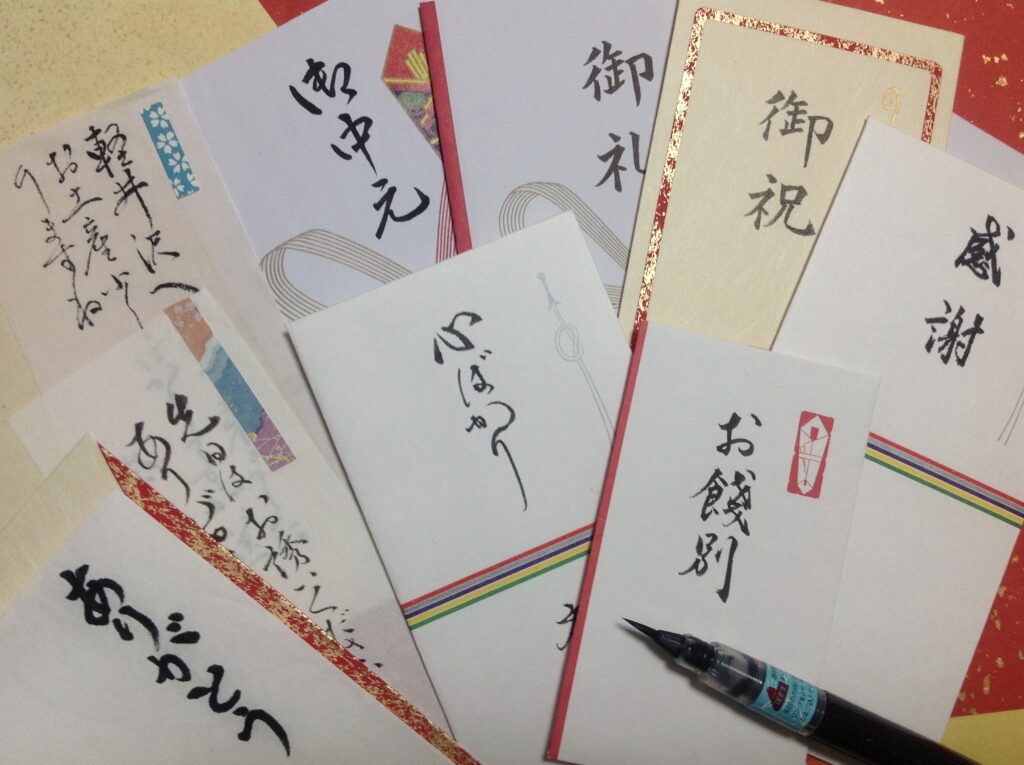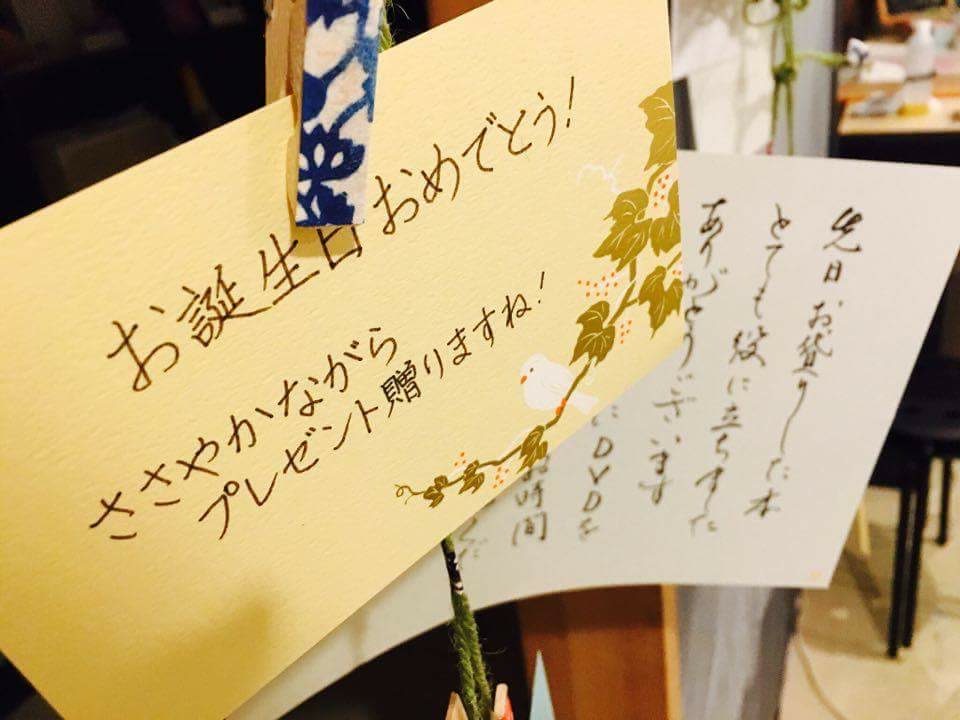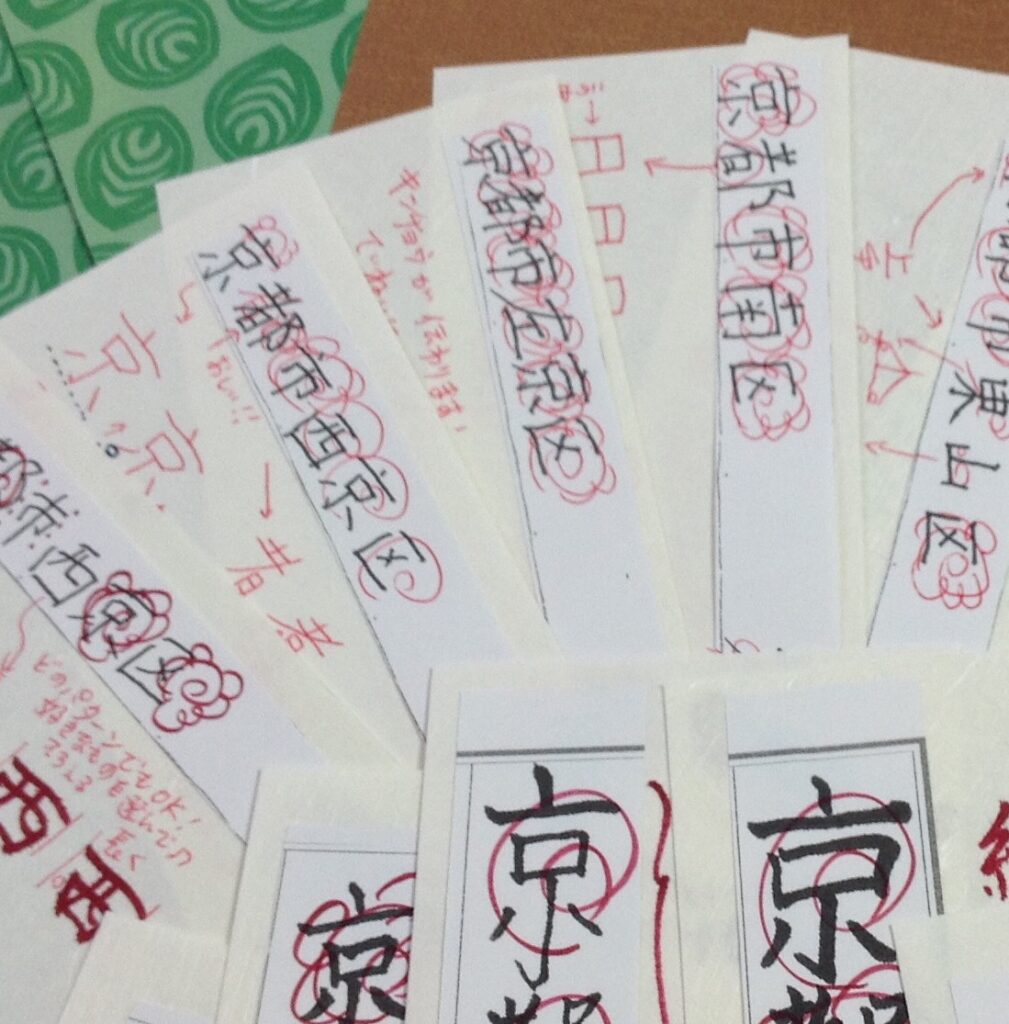
筆文字デザイン・サイン作成
書家・KISEN-髙橋琦泉-
Calligraphy design
企業、店舗、商品などの筆文字ロゴ・題字・屋号、
商品パッケージなどの筆文字ロゴデザインについて承っております。
毛筆デザインとセットで水墨画での挿絵や文字を絵にするなども可能です。
このほか、
企業理念、イベント使用のタイトルなどのほか、
個人様のお名刺、命名書、手紙代筆や贈り物などのラッピングデザイン、
WEBサイトのタイトル、SNSのプロフィール画像やアイコンデザインなど、
さまざまなご要望に合わせたオリジナルデザインをご提供し、
魅力を最大限に引き出すお手伝いを
みなさまのご要望に応じて、心を込めて制作しています。
Name design
手書き文字のシーンはデジタルが席巻して、ペンや筆を持ち、筆記する機会は減っています。
しかし、ご自身で名前などをサインする機会はまだまだあり、文字を書き残すことが貴重になっていることから、
丁寧に美しくおしゃれに書きたい、残したいと、ご要望が多く寄せられております。
はじめに、ご依頼者様の筆記を拝見させていただきます。
そのうえで要望を丁寧にヒアリングして、本来の文字やクセを生かしつつ、運気や縁起なども意識し、
一緒に相談しながらサインを作っていきます。
個性的で、品がある魅力的なサインデザインを実現し、書けるようになるまでお手伝いを致します。
Kisen lesson
美しく魅力ある書の世界に触れながら、書の楽しいレッスン、ワークショップ、セミナーを開催しています。
書を通じて創造性や感性を磨き、新しい表現力を身につけるレッスン講座、 文字を知るを楽しむ講座、歴史のあの文字、
道の書ー看板からー、武将の美しい書簡、など文字にまつわるワークショップ、
かな文字を知ろう書こう楽しもうセミナー、
インテリアにとけこむ筆文字デザインセミナーなど
楽しめるレッスン、ワークショップ、セミナーを行っております。
Kisen profile
髙橋琦泉(takahashi kisen)
書と水墨画、篆刻(印) 日本の伝統美、和の心を大切にし、ダイナミックで力強い線の中に、やすらぎのあるやさしい線をブレンドした表現がご好評いただいております。 驚きと感動をつなぎ、「心により近く寄り添う」をテーマに書画作しています。
筆文字ロゴデザイン、書と和の空間デザイン、サイン作成のほか、
美術協力・監修・書パフォーマンス、書道・筆文字・ペン字・墨象に関するセミナー、
ワークショップなど、筆文字・ペン字など筆記に関するさまざまなご依頼をお引き受け致しております。
筆の動き、少しでもご覧いただけたらと思い掲載しております。